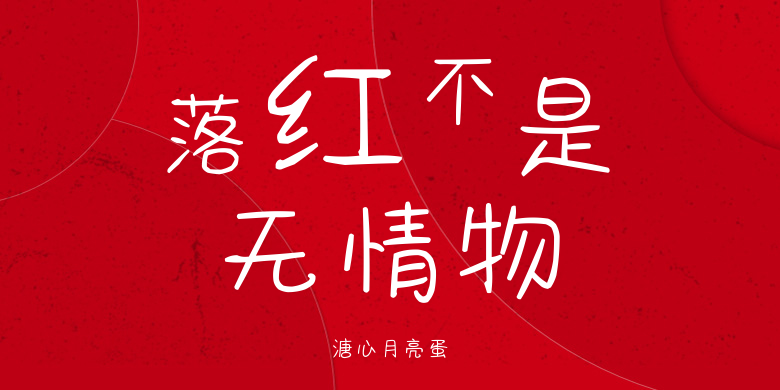
溏心月亮蛋
溏心月亮蛋,这款字体结构工整、笔画清晰,兼顾美观与易读性,适用于标题、正文、海报、包装、LOGO 等多种场景。字形优雅稳定,风格百搭耐看,适配日常排版与创意设计,让文字呈现更舒适、更具质感。溏心月亮蛋一笔一画,皆是细节,以均衡的比例、流畅的线条打造舒适视觉体验,字形端正大气,风格简约现代。无论是商业设计、品牌宣传还是日常排版,都能轻松驾驭,让文字更有格调与力量。溏心月亮蛋字体下载。